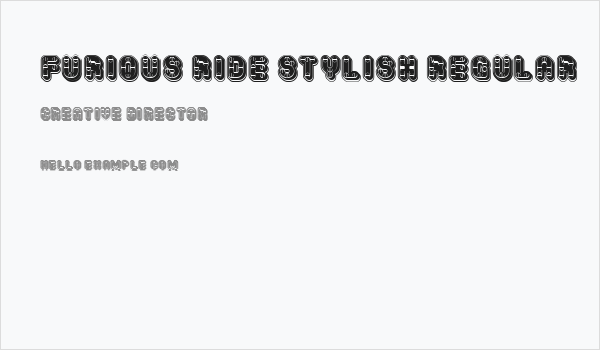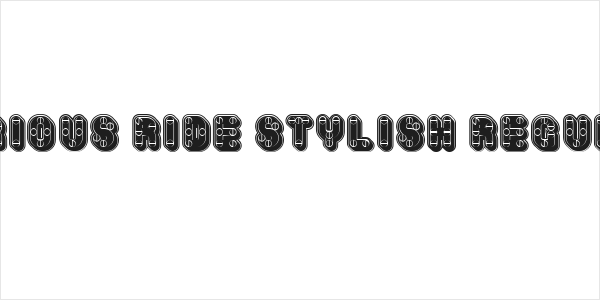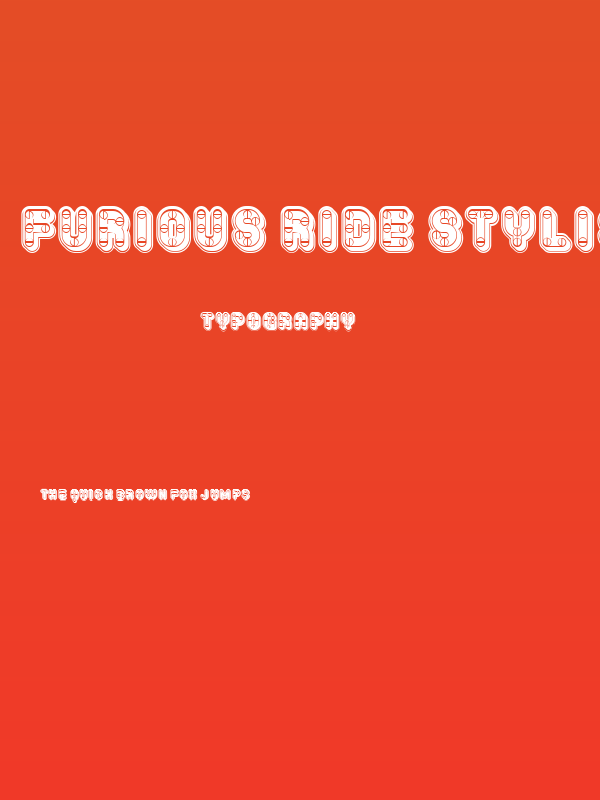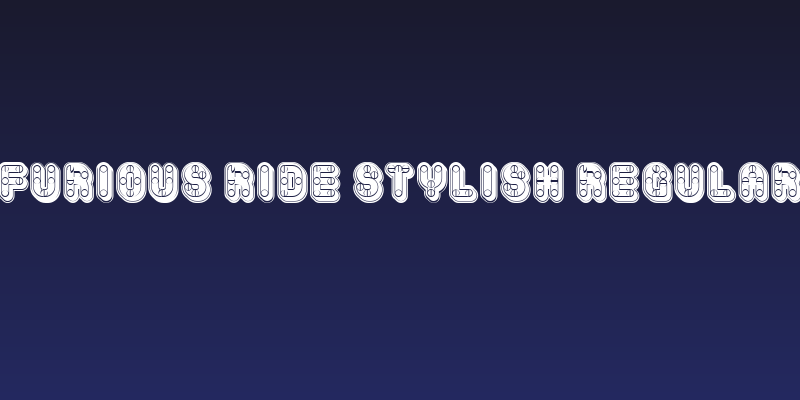
Furious Ride Stylish Regular Font
| Progetti proposti | Ideal for branding, posters, album covers, and any project needing a bold, modern aesthetic. |